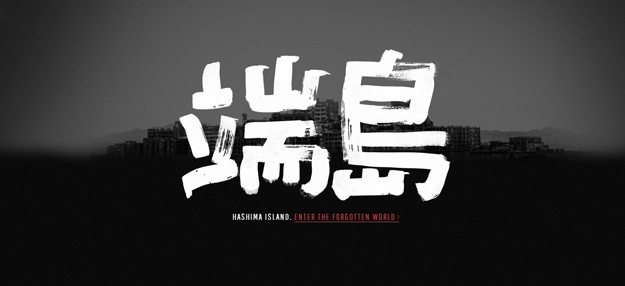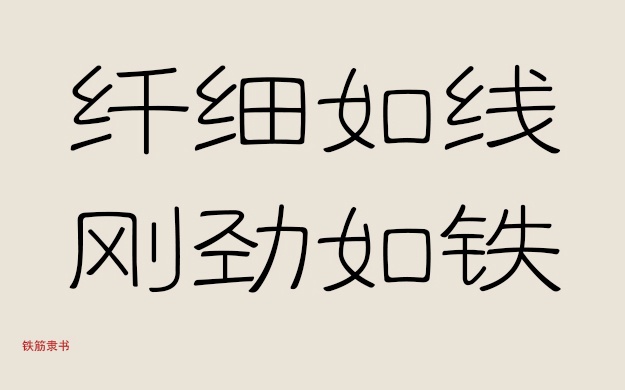
字体的性格
我们常用“字如其人”来形容一个人的字迹,也就是说一个人的性格和阅历会投射到文字上。而字体正是文字的性格,是文字表意功能之上的美学体现。优秀的字体远在读者理解句意之前就通过字形与笔画风格将情感传达给读者了,所谓“未成曲调先有情”,传情达意正是字体设计的意义所在。
千人千面,每个人的性格都不尽相同,字体也是如此。蔡邕的《笔论》中讲到:“若虫食木叶,若利剑长戈,若强弓硬矢,若水火,若云雾,若日月”说的便是字体的变幻无方。字体的性格多种多样,具体便体现在不同的笔画粗细、线条曲直、架构疏密等方面。接下来我就从这些维度来粗浅地分析一下字体的性格。
粗与细
笔画粗则浑厚、浓重、有力,如雷霆万钧;笔画细则单薄、轻巧、纤弱,似弱柳扶风,这是一种最直接粗浅的观感。
粗笔画字体在排版上会形成高密度的文本块,这是因为笔画加粗,字体的负空间就会减小,视觉面积加重,产生一种压迫感,进而在整个版面中凸显出来形成视觉重心,产生强调的作用。所以粗体字经常用于标题和标语上,占据显眼的位置,产生强调的作用。
如果说粗体是彪形大汉的一声断喝,那么细体则是小家碧玉的吴侬软语,娓娓道来。细笔画字体在视觉面积上较淡较轻,缩小了视觉面积后,笔画负空间增大,结构显得疏朗清透,较小的视觉分量亦不会让读者产生压迫感。
曲与直
字体笔画的曲直走向赋予了字体力量和弹性。直线是峭壁、落石、参天古木,或是茫茫平野、千里阵云,直来直往的线条代表了坦荡、干脆、果敢,但也可能意味着死板与偏执。直线赋予字体的是一种阳刚的气质,那么曲线就代表了阴柔的一面。曲线是柔丝、浮云、蒲柳,是九曲回肠,更多了一分包容与婉转。
绝大多数字体并非是由单纯的直线或者单纯的曲线构成,横竖为直,撇捺为曲,有曲有直才显得刚柔并济,有力量,也有弹性。比如北魏楷书起笔处与转折处皆如削金断玉,干脆利落,整个字体也就显得挺拔刚健、英气勃勃,在撇与捺处又有优美的曲线,多一分圆润,也就多一分飘逸灵动。
而超刚黑则是一款典型的纯直线型字体。粗壮的笔触加上凌厉的线条,使字体有着一种不容置疑的坚决态度,去掉了曲线,也就没有了一丝回旋的余地。
任何理论都会有特例的情况,比如说铁筋隶书虽然绝大多数笔画都是曲线,却处处透着力量感。虽纤细如线,却刚劲如铁。本质上就是因为它的弧度都是有弹性的,将弧度加入横画,非但不减刚劲,反而会有一种反弹的力道。
松散与严谨
日常生活中的文字书写显得轻松活泼,有一种随性不羁之美。而文字书于庙堂、铸于钟鼎,或者付梓成书、传于后世,则是有一种严谨端庄的美。其本质的区别则是结构的松散与严谨之分。
天真活泼是少年心性,儿童的世界没有太多的规则约束,儿童的字体也显得稚嫩活泼。所以结构松散的手写体经常运用在儿童题材或者轻松诙谐的阅读环境。
楷书顾名思义有楷模之意,方正俊雅,法度精严。它也象征着传统儒家文化中为人的标准,品行端方,刚正不阿。所以结构严谨的楷书常用于庄重的书体或者碑铭。
简与繁
这里所说的简与繁并不是简体与繁体,而是笔画细节的复杂程度。举个最简单的例子,衬线体相对来说要比非衬线体细节复杂一些,宋体也比黑体复杂一些。正如花纹繁复华丽是古典家具的典型特征,简洁实用的宜家家居是现代生活的典范一样,字体的繁复与简单一定程度上也代表着古典与现代走向。
Trajan Pro是一款古罗马风格的字体,衬线处细节丰富弧度优雅,线条粗细程度不一,最初是刻在古罗马的石柱上,有着浓厚的历史沉淀,因此常用作古典题材的电影海报。
Helvetica被视为现代主义在字体设计界的典型代表,是一款经典的无衬线字体,剥除了多余的细节,以标准的几何形体做结构。反而是这种没有任何风格的字体形式成为了一种风格。简约,现代,因此常用于现代企业的logo设计、杂志排版、导视系统等。
工具
不同的书写工具会赋予字体不同的性格,毛笔赋予字体丰富的质感和多变的线条,或婉若游龙,或势若雷霆。
毛笔赋予了字体柔美温润的特性,刻于碑石上便又融入了刀法的特点,线条便又有了锋芒。
甲骨文和金文属于同时代的字体,但是甲骨文需要在卜卦之后迅速刻在龟甲上,有一种率性不拘的美。而金文要铸造在青铜器,置于庙堂之上,所以结构严谨规整,有一种庄严神圣的意味。工具载体不同,风味也不一样。
现代电脑辅助制图赋予了字体线条的精确性,组成部件的标准化,使字体有了现代时尚的特性。但比之其他工具又少了一些质感和灵动性。
所以字体设计并不局限于电脑屏幕或者纸笔,去尝试不同的工具就有无尽的可能性。
借代
汉语中经常会有借代的手法,巾帼指代女性,须眉指代男性,是一种高度概括的手法。汉字是象形文字,“山水日月风雨雷电”皆是对自然万物高度的象形概括。现代的字体设计又在基本的字形之上将其他事物的特性融入到字形中,这也是一种常用的字体设计的手法。
剪纸体将民间传统的剪纸艺术融入了字体中,角度错落,笔画之间做了粘连处理。不规则的线条显得俏皮、轻松,又掺杂了一些传统文化特色。
电影《可可西里》将藏文字体的风格融入了中文字体中,使得字体有了一种异域风情。
借代是将一件事物的性格借到设计中,常常会成为一件作品的点睛之笔,处理得当将会有四两拨千斤的效果。善用借代也是给字体更多可能。